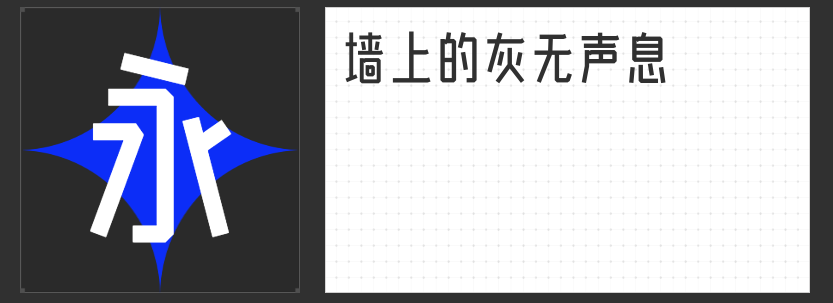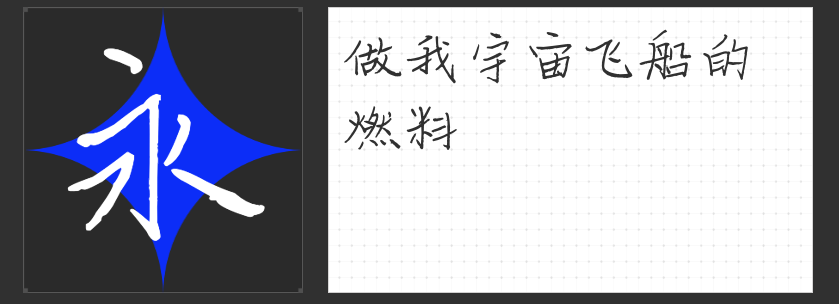
醒图合作精选字体推荐:塑造视觉新风尚
在视觉设计领域,字体不仅是信息的载体,更是情感与风格的传递者。醒图,作为创意设计的先锋平台,携手四款独具魅力的字体,为广告设计、平面设计、印刷包装及多媒体创作等领域带来全新的视觉体验。今天,就让我们一同探索这四款与醒图合作的精选字体,它们各自以其独特的风格与魅力,为设计作品增添无限可能。
1. 励字玉树临风简:质朴之美,静谧之选
在纷繁复杂的视觉环境中,“励字玉树临风简”以其瘦长的字形、修长端正的姿态,展现出一种朴实无华而又内敛的美感。这款字体拙中见巧,每一笔一划都透露着质朴与纯粹,仿佛是大自然中最质朴的风景,静静地诉说着故事。它非常适合用于广告设计、平面设计、印刷包装以及正文标题,能够营造出一种宁静致远的氛围,让设计作品在喧嚣中保持一份难得的平和与雅致。
2. MyFont凌渡哥哥简:童趣手绘,温馨自然
当卡通遇上字体,“MyFont凌渡哥哥简”便是一场完美的邂逅。这款字体专为满足更多展示效果而设计,整体风格舒适自然,笔画间流露出童稚可爱的韵味。点、横、撇、捺的不规则弧度,如同孩童笔下的涂鸦,既柔软又亲切,让人一眼难忘。无论是标题、正文、宣传语还是品牌标准用字,它都能以其独特的形态与内容的完美结合,为设计增添一抹温馨与活力,让信息传达更加生动有趣。
3. 励字造梦简 常规:城市天际,力量之美
“励字造梦简 常规”以其左侧倾斜右侧竖直的不对称设计,模拟了摩天大楼的宏伟与壮观,让人仿佛置身于繁华都市之中,抬头仰望那令人震撼的建筑群。这款直线型字体,力量感十足,棱角分明,字形轮廓清晰有力,是展现现代都市气息与力量美学的绝佳选择。它适用于需要强调力量、速度与未来感的设计项目,如科技展览、建筑宣传等,能够瞬间提升作品的视觉冲击力。
4. 励字星宜简:圆润天真,童趣无限
“励字星宜简”以其独特的笔画拼接感和厚重的笔画设计,展现了一种天真稚拙的美感。起落笔及拐角的圆形处理,使得整个字体看起来柔和而自然,充满了亲和力。这款字体非常适合用于标题、海报、卡通等场景,能够轻松营造出一种温馨、欢乐的氛围,让设计作品更加贴近受众的内心,激发共鸣。
每一款字体都是设计师情感的延伸,是创意表达的媒介。与醒图合作的这四款字体,不仅各具特色,更能在不同的设计项目中发挥各自的优势,为作品增添独特的视觉魅力。无论是追求简约质朴,还是渴望童趣温馨,亦或是强调力量与未来感,这些字体都能成为你设计旅程中的得力伙伴,共同创造出更多令人瞩目的视觉佳作。选择适合的字体,让设计因字而生动,因情而感人。